陈幼坚是谁? 始于1960年代的艺术旅程
由白石画廊主办的陈幼坚首个画廊个展《陈幼坚是谁? 始于1960年代的艺术旅程》于2019年1月至2月在香港举办。
本次展览是陈幼坚在香港的首次个人纯艺术展,按照时间顺序展出由他最新作品到远及上世纪60 年代从未曝光的沧海遗珠,呈现包括平面艺术、摄影、装置及数码艺术等视觉媒界,甚至他在青少年时期创作的一些珍贵手稿。
1950年便受到中西文化熏陶的陈幼坚,二十岁开始接触广告行业,同时问道东西汲取精华,他的「东情西韵」设计艺术风格別树一帜。自上世纪七十年代中期以来,陈幼坚经历及见证自1979年中国开放改革、日本战后的经济奇迹;周游列国也让他从欧洲文化遗产吸收历史美学,这些点滴都刺激感性的他,并转化为自家美学基因与创意点子,他以陈式视觉语言将大都市与旧城跨文化融汇对话,将商业设计提升至艺术层面,突破设计的条框。
陈幼坚的美学、艺术设计与创意曾在不同的视觉空间及回顾展中呈现,包括日本Ginza Graphic Gallery (2002) 、香港文化博物馆(2003) 、上海美术馆(2007)。各个本地、海外博物馆甚至双年展均见到他的踪影,例如2002年及2006年的上海双年展;他更两次入围香港当代艺术奖(2010 年及2012 年)。
陈幼坚学生时期创作的《一梦》(1970)反映当时社会受流行文化的影响;《英雄所见略同》(2006)则解构超级品牌「竞争对手」之间错综复杂关系之余,又诠释各自的市场策略;《iEye 爱》iPhone 摄影系列(2012)是他于旅行瞬间抓拍的视觉日记,体现当下社会的生活百态与不同文化脉络。
透过视觉语言、多维度的图像和形式,观众可看到陈幼坚不断演变的生活艺术与人生哲学。影像作品《京都我的爱人》(2013)、《人生角度一线之间》(2016)和《Hello Ginza!》(2017)均为他的最新实验媒介,试图将艺术拉近生活。
从平面到立体,展览会让观众重新认识陈幼坚的艺术美学,并透过回顾陈幼坚40多年来持续不倦的创作之旅,重新认识「陈幼坚是谁?」
就本次展览,Design 360°与陈幼坚先生进行了访谈,从展览出发,谈论他的作品以及之后的计划动向。
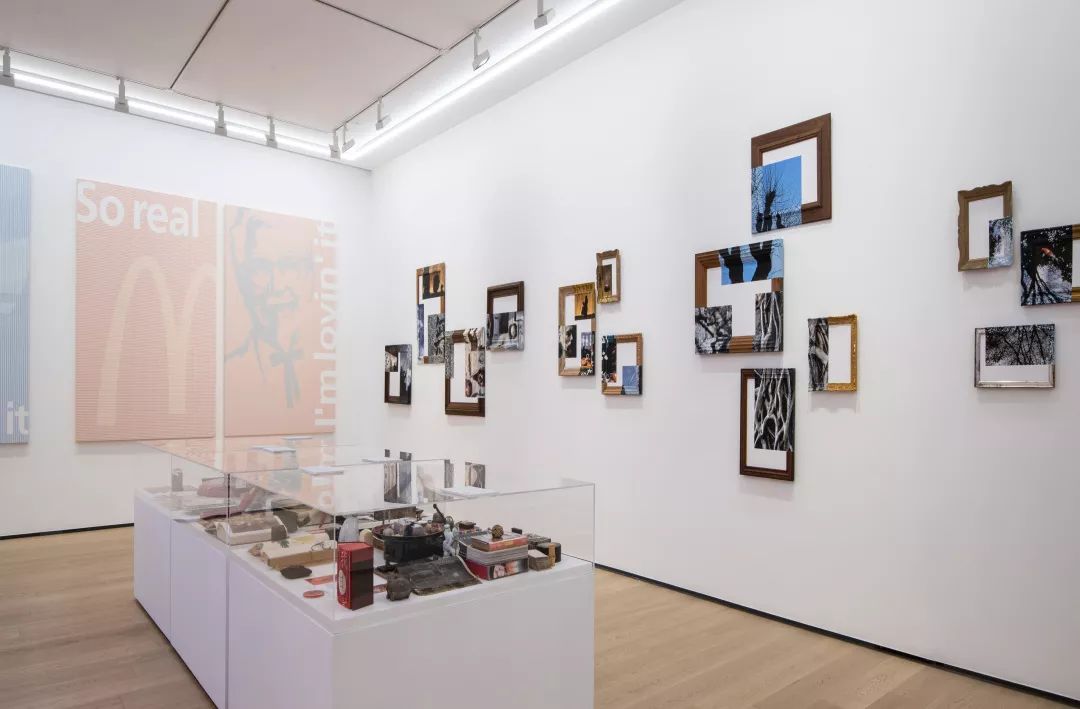
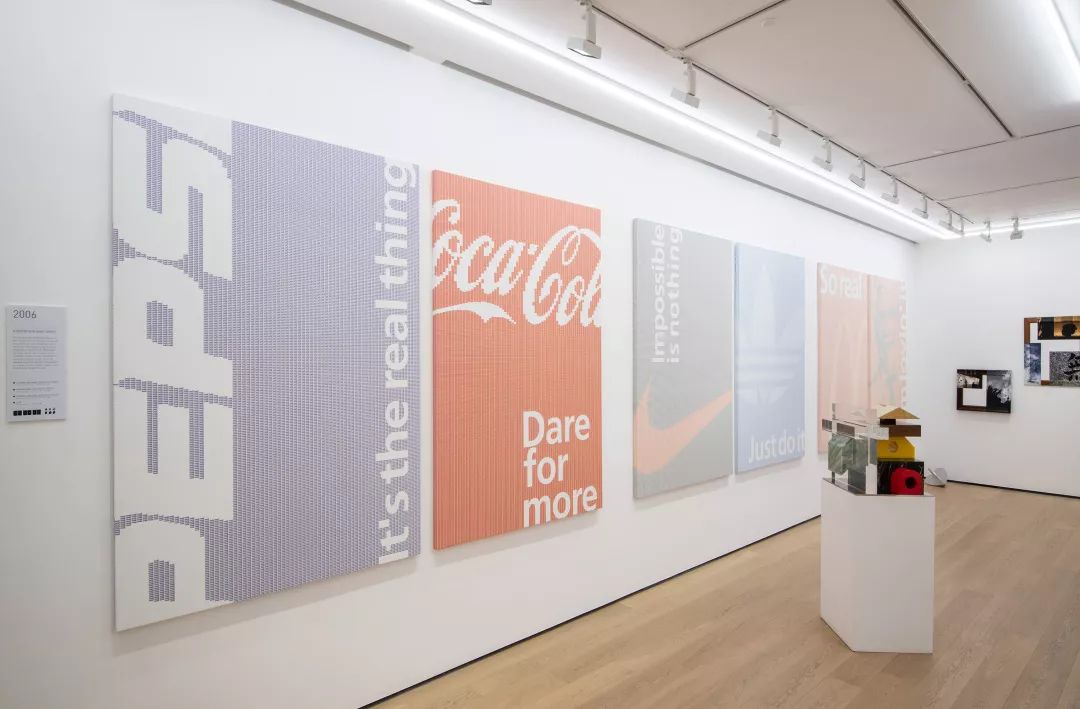
Design 360° : 请问可以介绍一下本次展览的策展理念吗?这次展览主要是围绕怎样的主题和线索?
陈幼坚 (Alan Chan) : 创意工作48年来,从做广告到设计,很多人知道我是个设计师、是个偏重艺术文化的品牌顾问。但很多人不知道我也有艺术家特质,例如我有很多情绪能量、我固执,甚至激情(对于创作)。
所以回顾过往我的设计项目也都会看到融合了许多艺术及文化为底蕴的作品,透过这次展览希望让大家更加深层地理解我于创作生涯经历的一些矛盾;即使工作本质面对一个瞬息万变的商业环境。
我还是坚持将我的理想主义借由不同创作媒介表现出来,所以今次我希望与大家分享陈幼坚的另一面。因此将首个纯艺术画廊个展主题定为《陈幼坚是谁? 始于1960年代的艺术旅程》。
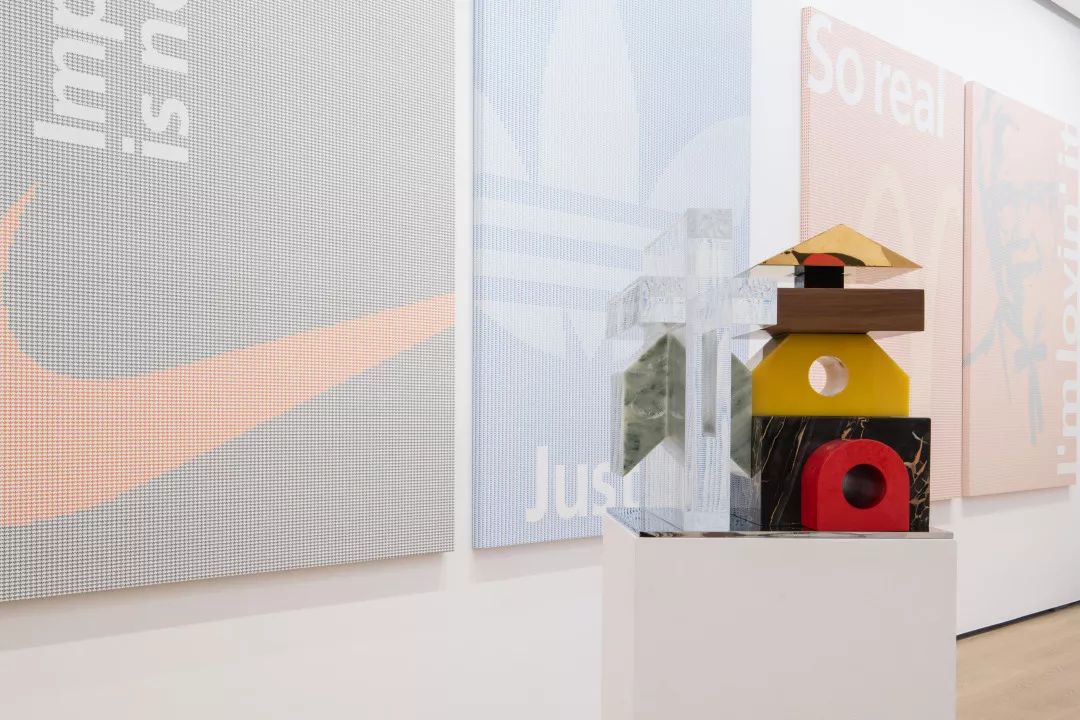
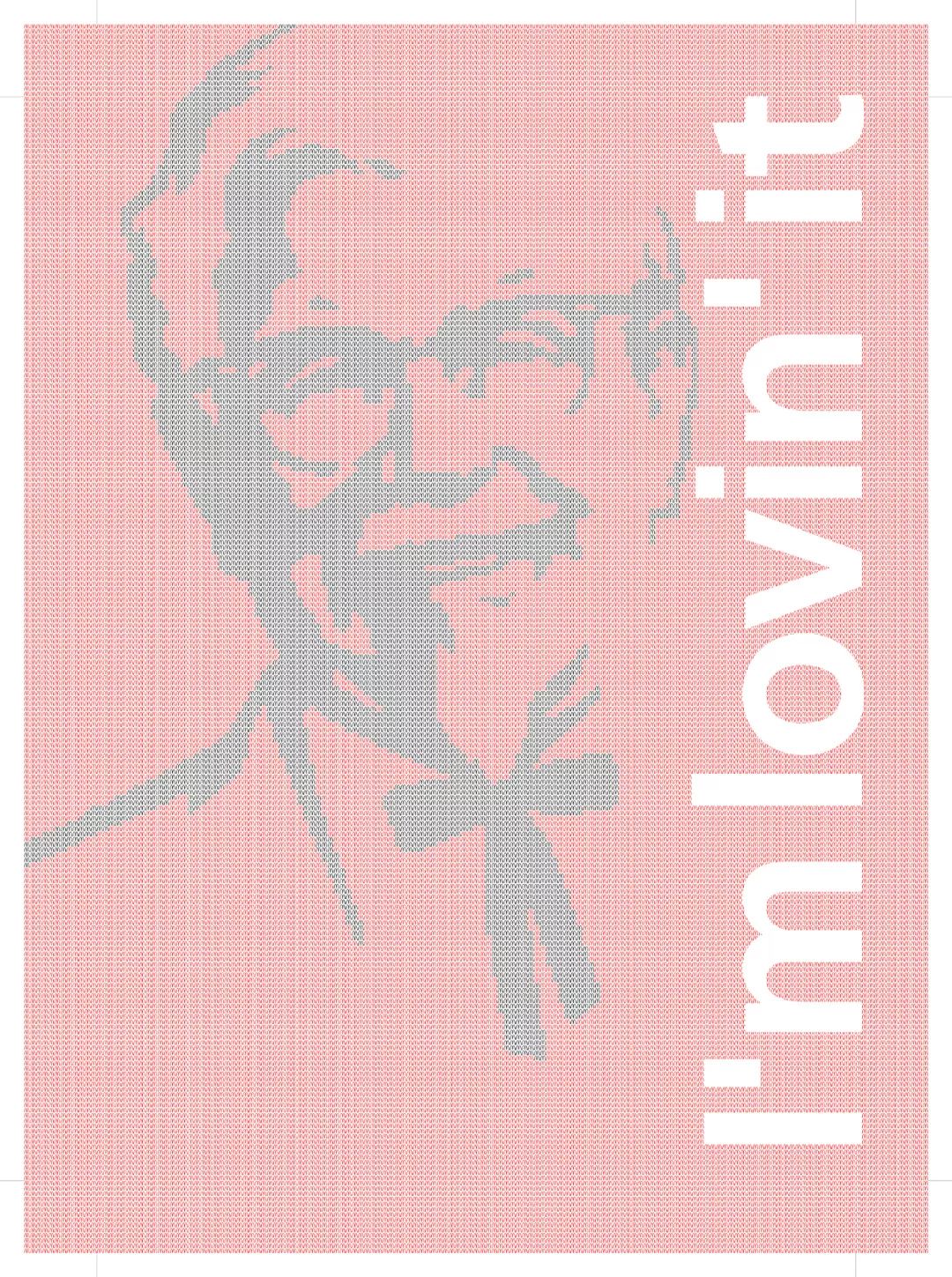
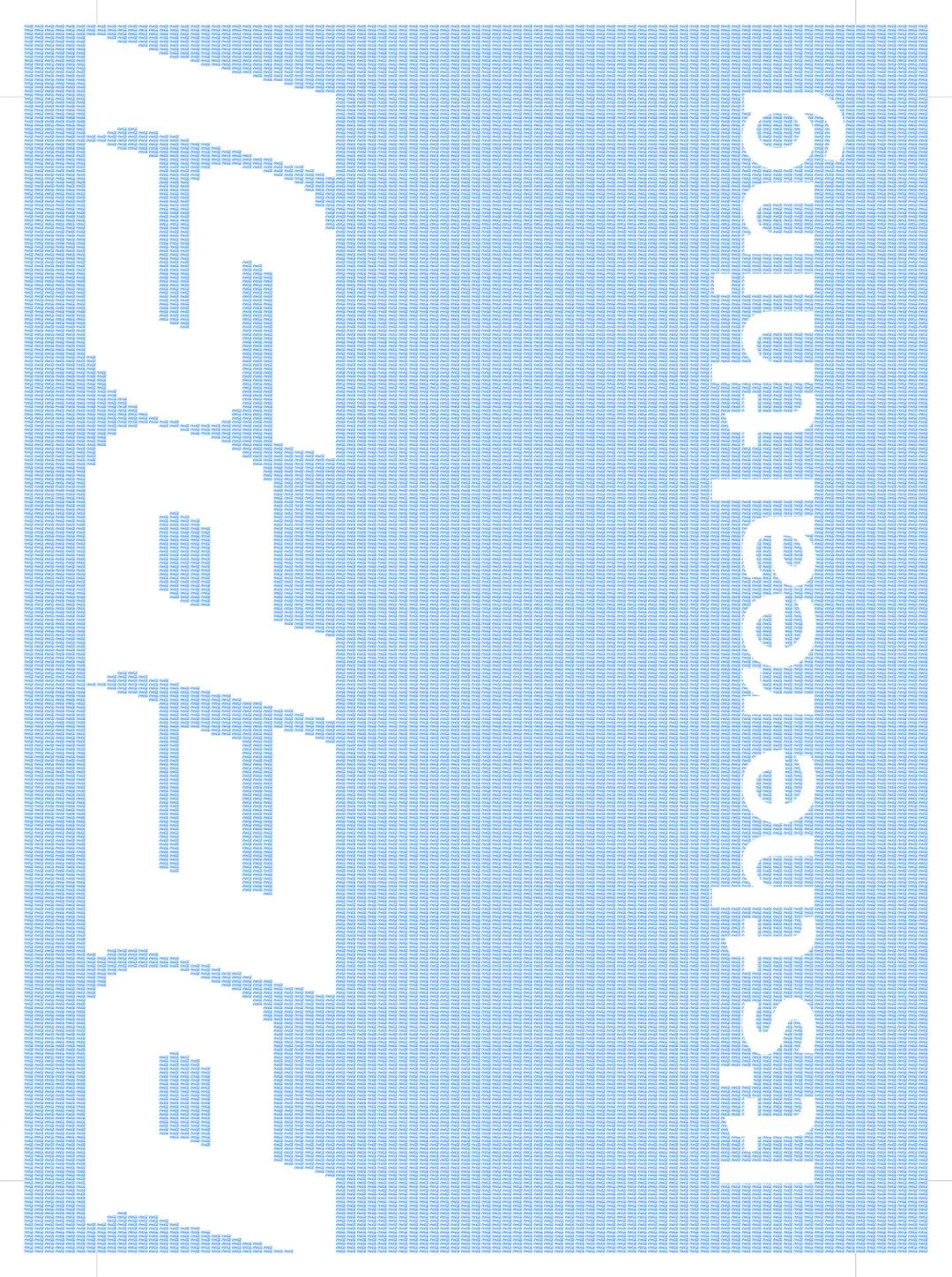
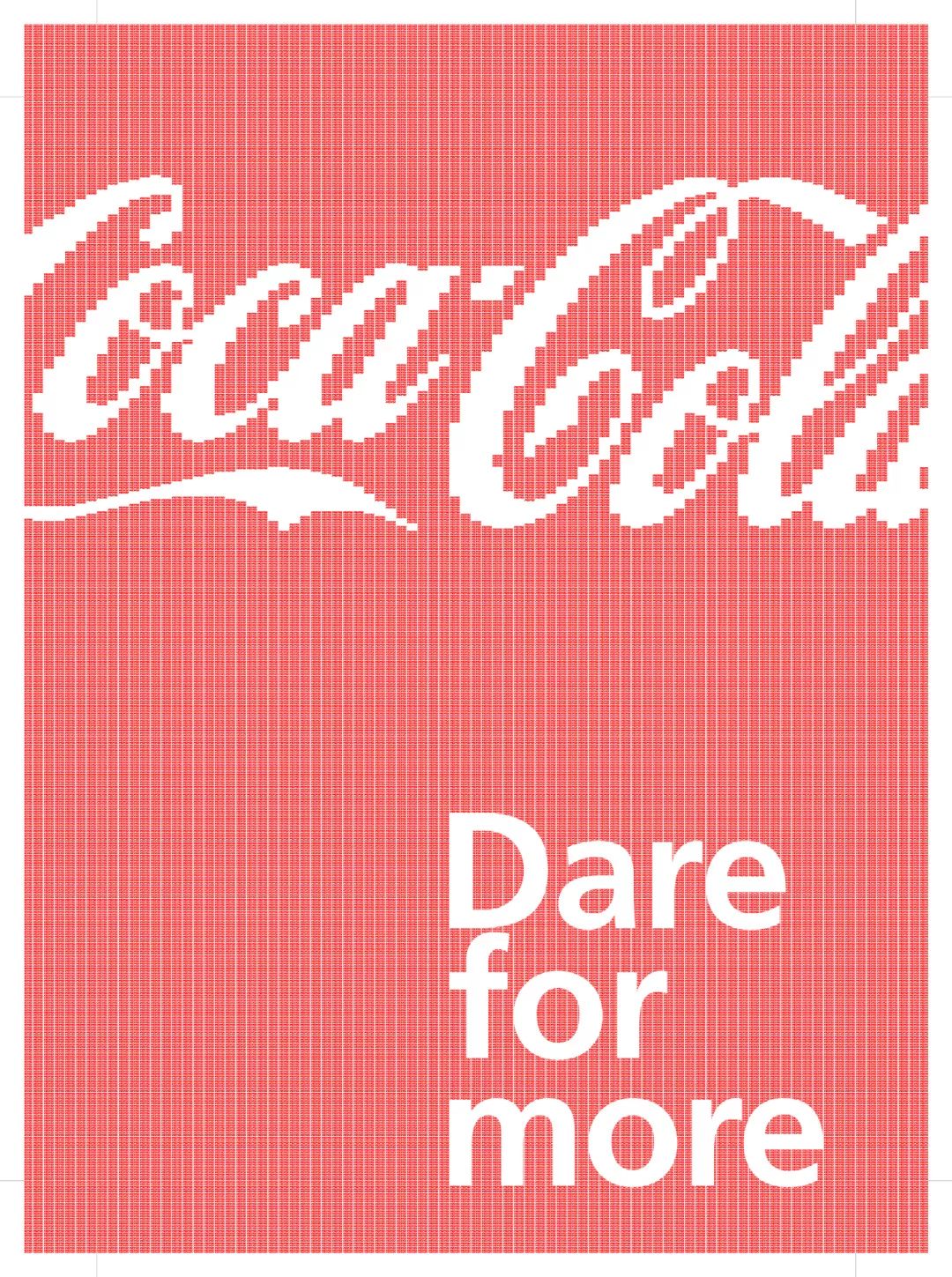
A Brand New Game (KFC ×Pepsi)& (Coca Cola × McDonald's)
Design 360° :相比起您以往的个人展览,本次展览有什么与别不同的地方呢?是什么原因驱使您举办本次个展?
陈幼坚 (Alan Chan) :本次展览分为三个空间,分别展示从平面到立体不同时期的艺术创作。墙上呈现的是我艺术方面语言(即创作),另外为了阐述创作的源头,画廊空间内设置了六个展示箱。展出我不同时期的收藏、影响我创作的人、事物和对我极为重要的代表物件,让观众更了解我的灵感来源。
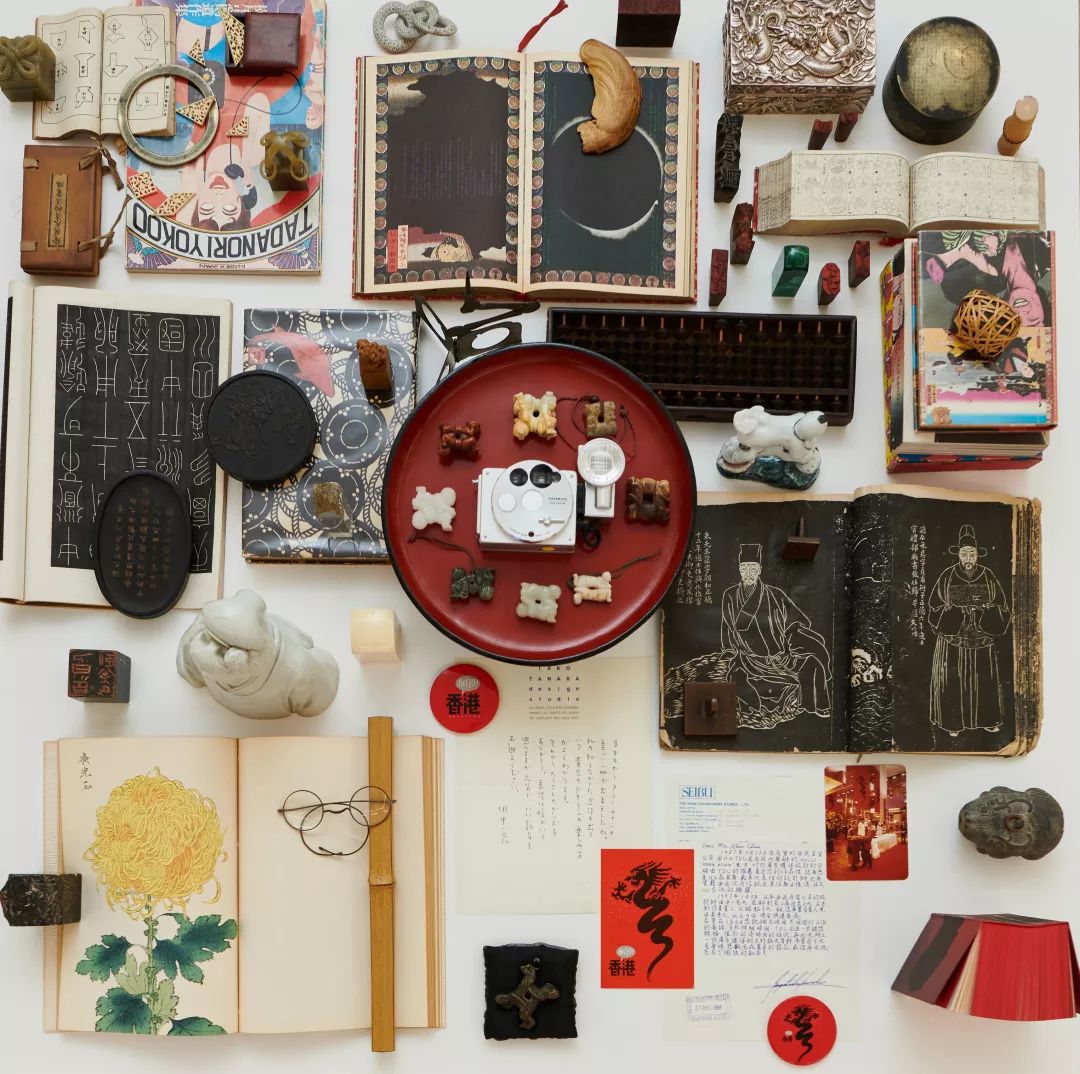
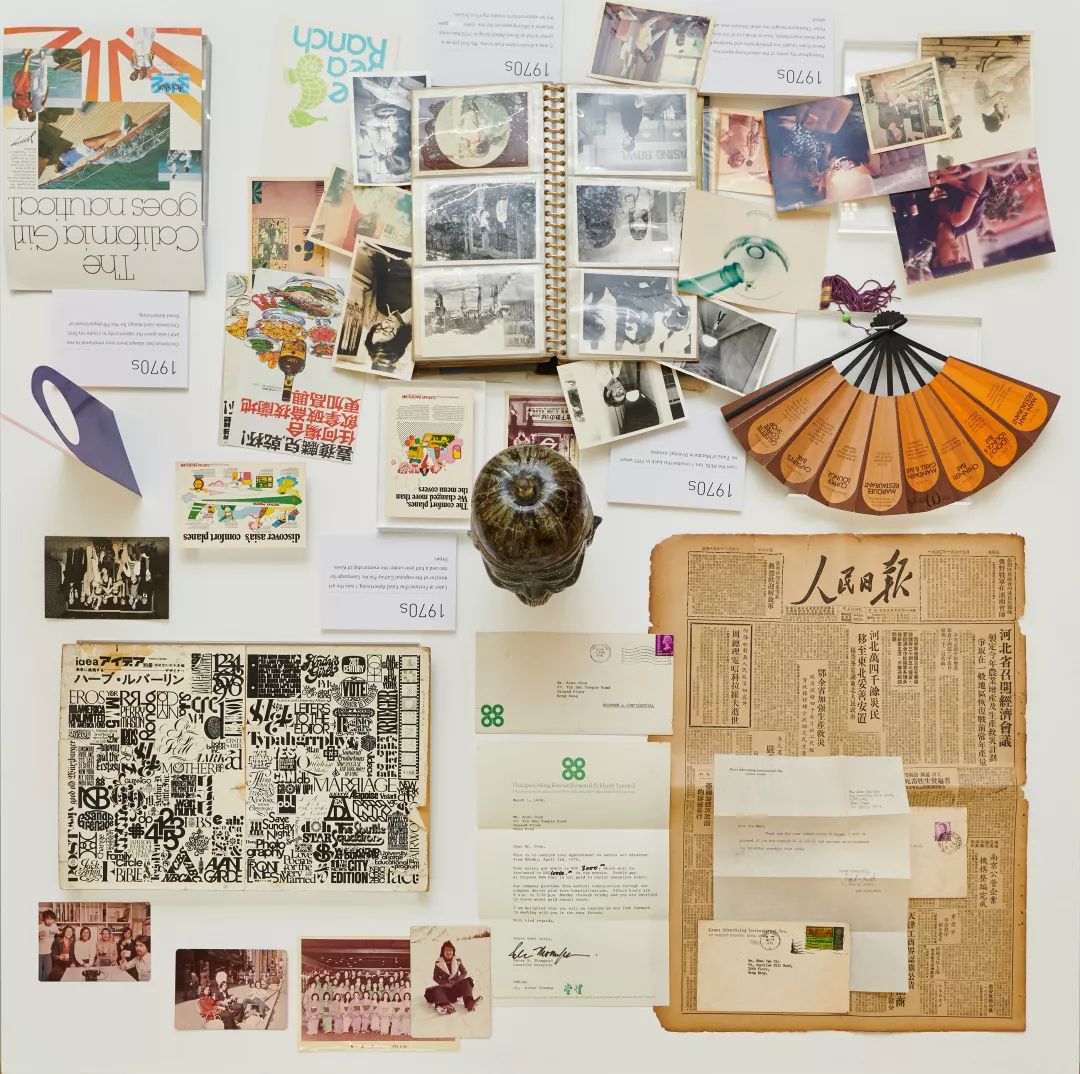
Design 360° :本次展览有哪些展出的作品或事物是您觉得特别有意思或想推荐的吗?能同时分享一下作品/事物背后的故事吗?
陈幼坚(Alan Chan): 由于这次展览核心是一个陈幼坚创作旅程的回顾,加上受到极具分量的日本白石画廊邀请,成为其代理日本艺术家之外的首位香港艺术家,我也为了这次展览完成全新系列的作品,希望将香港艺术家的风格突显出来。
全新创作《Enlightenment》是受到汉朝与唐朝书法家的字帖启发创作,代表我受到世世代代书法家的“启蒙”(Enlightenment),我认为从不同艺术家身上看到学到的,不仅是技艺,也是做人做事的道理,所以书法字帖里蕴含了大量的智慧,我从中取出两个不同书法体的“光”字制作为香港常见的霓虹光管,将表象的光字点亮的同时,也点亮脑中的那盏灵光,试着表达我钟爱中国书法的艺术之美。
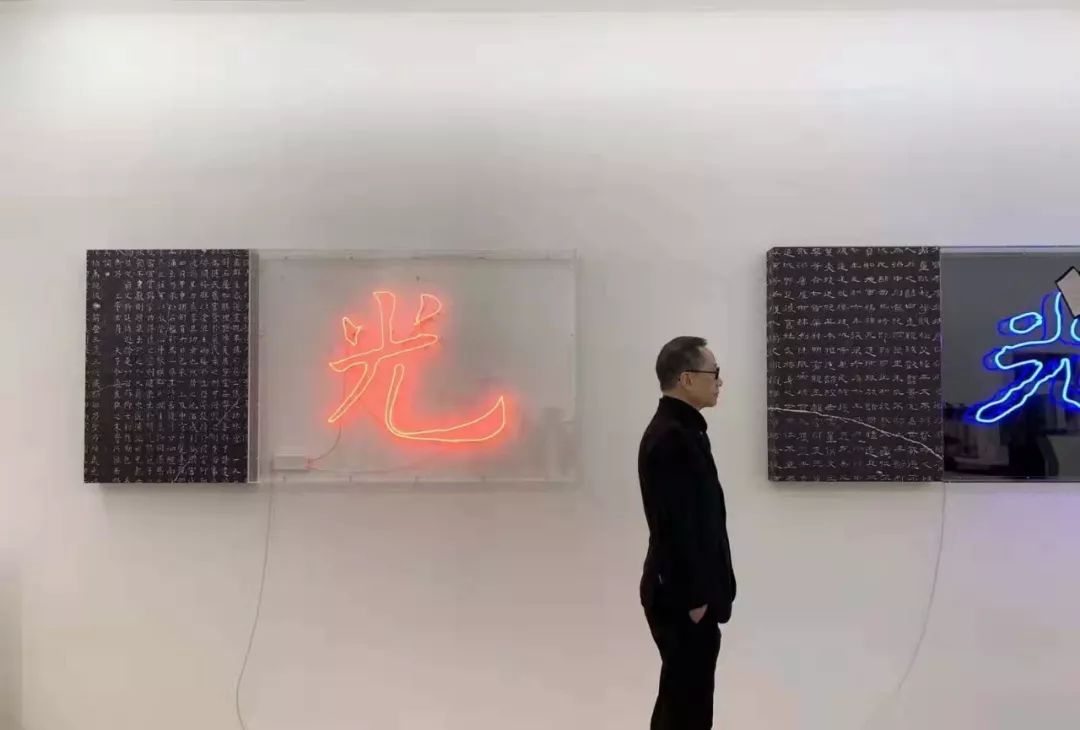
Enlightenment
另一个系列《Connection》是继2016年曾在香港巴塞尔展出过的Paris Connection之后于今年全新的创作,不同于前次的创作,这次实谓“破格”创作。
我一直认为相框象征人眼,而唯一的区别是呈现状态── 静态和动态,将巴黎收集的古董框,不是先有画再有框,而是先有框再有画。《Connection》系列试图通过一批古董画框捕捉摄影混和绘画的生活片刻,从艺术家眼中看出的画面当下视线其实是浮动又连续的,而非静止又局限,这个系列算是我极为喜爱之作。
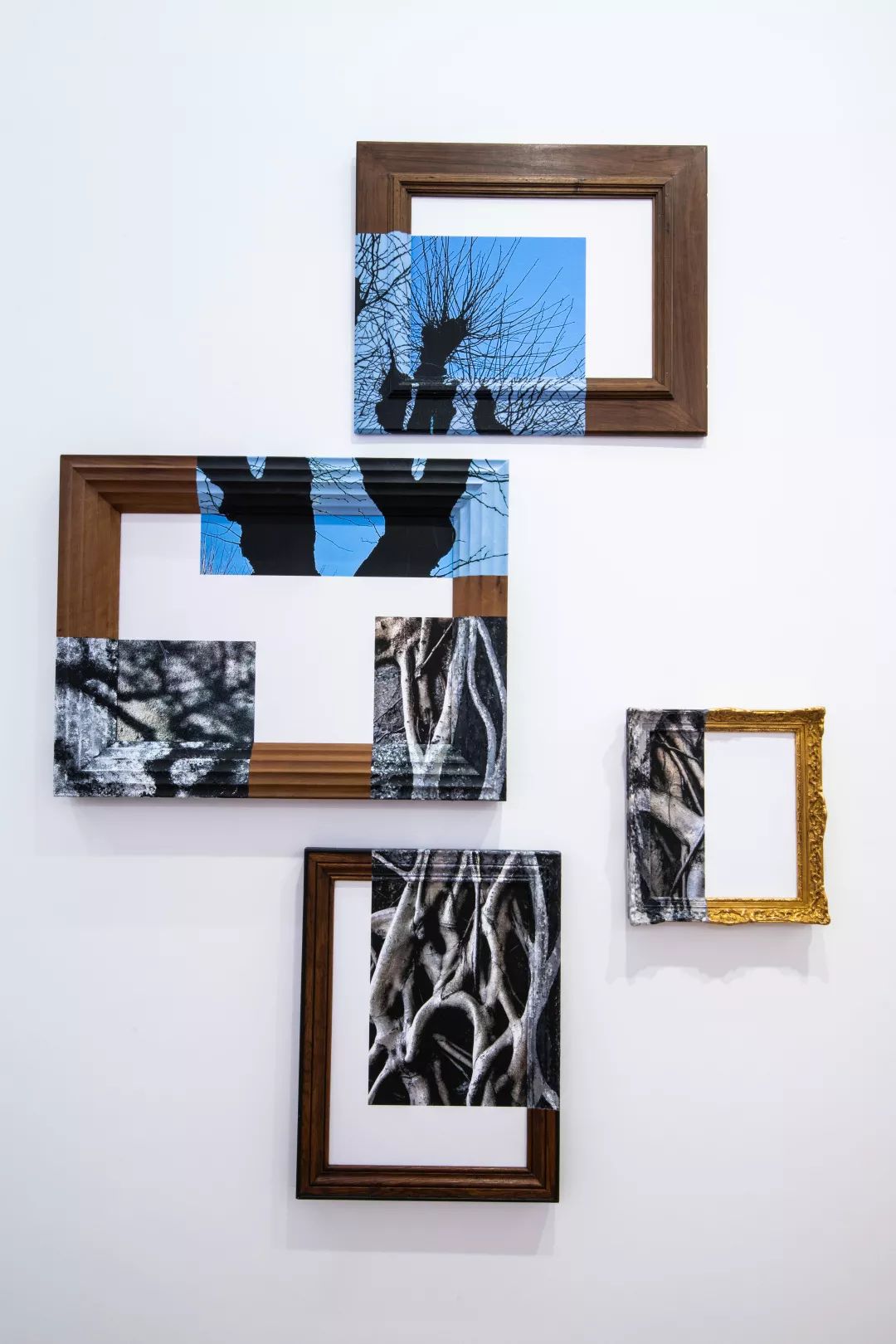
Connection
还有一组全新创作为《City Landscape》系列,这是向我的生长地香港致敬,也是我工作日常所见的城市山水景色。我在香港有个7000平呎的艺术文化空间,建于六十年代的工业大厦内,一年常常会举办多场设计与艺术活动,那些工厦的电梯内极度斑驳,每天我看着都觉得其纹理有趣,于是我拍下这些局部,甚至调成黑白,制作成卷轴落上印,成为我的现代城市山水画。
City Landscape
Desgin 360° : 本次展览名为“陈幼坚是谁”,从设计到艺术,从平面到立体,随着您的不断尝试,您的身份亦越来越多样。回顾您的创作生涯,对于“陈幼坚是谁”这个问题您会作出怎样的回答呢?
陈幼坚 (Alan Chan): “陈幼坚是谁”对我来说是个开放性的问题,因为我自己都估计不到是否下一步我会开始画油画、做雕塑,或者再有新的影像装置,所以我身为一个创意人不应该自己设限、定义框架,因此你可以说我是“无界、无限、随心所至”。
Design 360° :在这次展览里分享的作品及物件,除了是您个人创作及经历的一次回溯,亦能看出香港、甚至中国、日本、欧洲等文化的变迁。您怎样看待这些年来香港设计在这些文化影响下的演变及发展?您又怎样看待香港现在的设计环境呢?
陈幼坚 (Alan Chan): 如果身为一个外国人第一次来香港,一定会认为香港很迷人,充满各种创意活动,但身在香港,长久以来总觉得理所当然。所以我常希望以一个旅游身份体验香港的角度来观察,我觉得香港每日每夜都有新的事情发生,几十年来香港融合东西文化至水乳交融的程度。
即便亚洲其他城市从金融带动国际交流,都不似香港真正具有中西融合的国际大都会特质,不论经济面或者文化面。
Design 360° : 推出“杀手口红”、“中国茶香水”等个人品牌产品、进行艺术创作、推广艺术及设计等文化活动……您近年来进行了各式各样的跨界活动,踏过69岁的生日,接下来,您的创作及活动核心会在哪些领域呢?有哪些事情是您未来最希望做的呢?
陈幼坚 (Alan Chan): 想做的事情难以一言以蔽,但确实人生在世有一个非常想实现的梦想,就是希望成立一个设计艺术美术馆。将我毕身收藏的上万件设计与艺术品以完整的策展研究及深入介绍,展出于美术馆内。让大众有机会透过我的收藏由浅入深认识文化带来的生活智慧,也一探究竟我的花花世界。
杀手口红
中国茶香水 — CHÁN BY ALAN CHAN